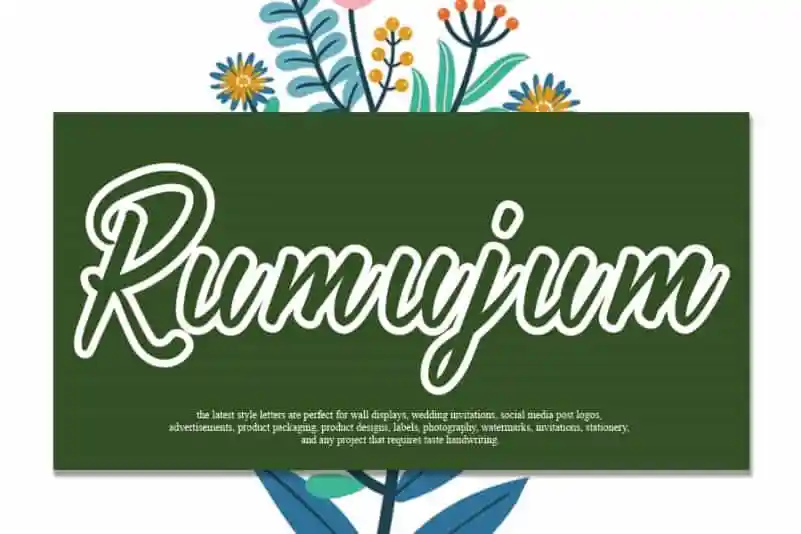
Rumujum Script Font – Fonte Grátis
Rumujum Script Font
A Rumujum Script Font é uma fonte escrita a mão que transpira emoção e elegância. Seu traçado fluido tem um toque refinado, perfeito para qualquer projeto pessoal ou profissional. Este script não apenas traz beleza, mas também oferece uma sensação de originalidade única e uma estética inovadora que se destaca no mundo dos design gráfico. Seja você um grafista experiente ou iniciante, Rumujum Script é a fonte perfeita para adicionar um toque único em seus trabalhos, transformando-os em designs surpreendentes e memoráveis. Sua forma elegante e distintiva faz dela uma escolha irresistível para aqueles que desejam incorporar algo realmente especial nas suas criações.